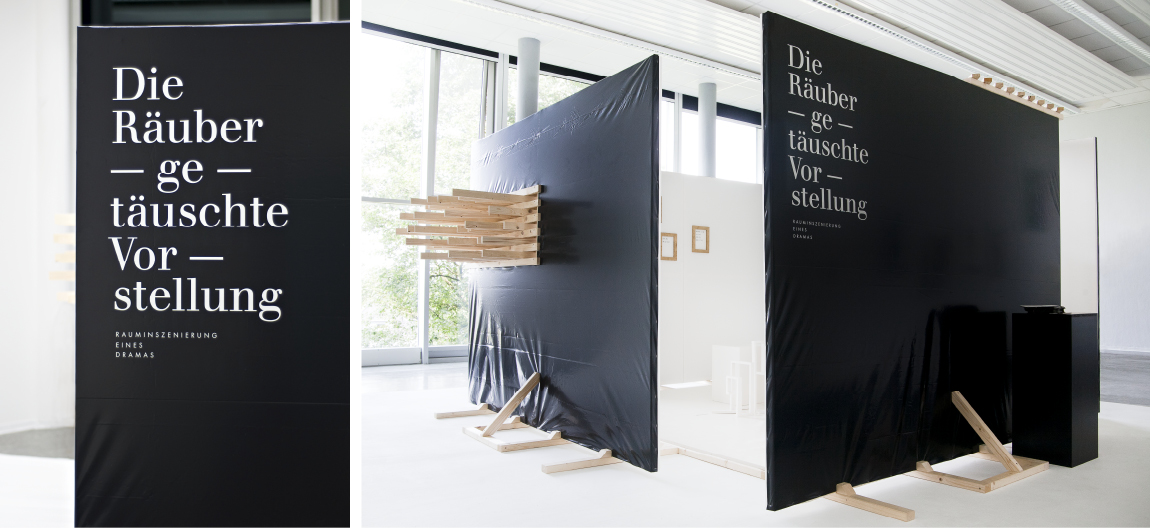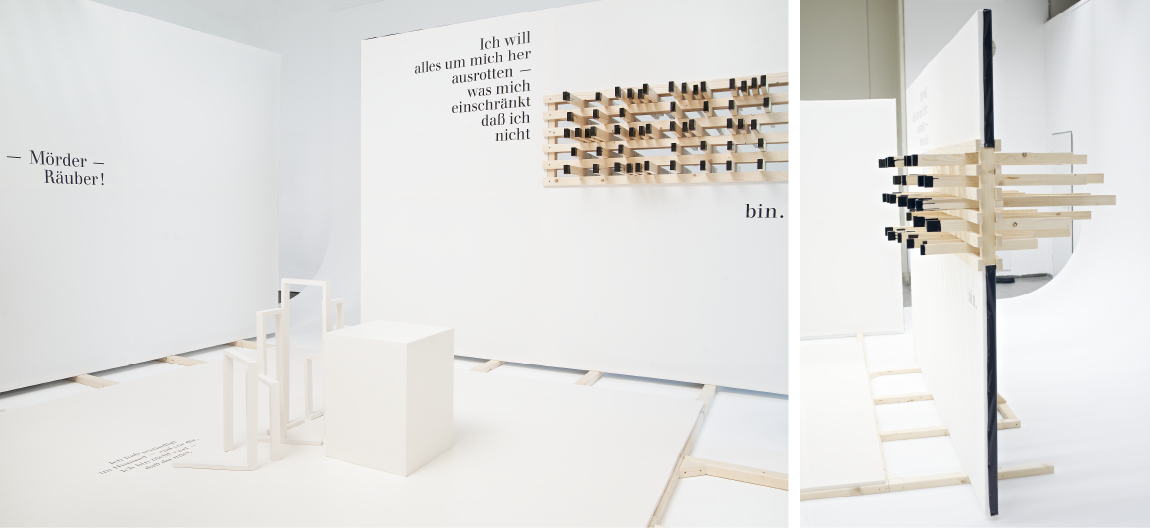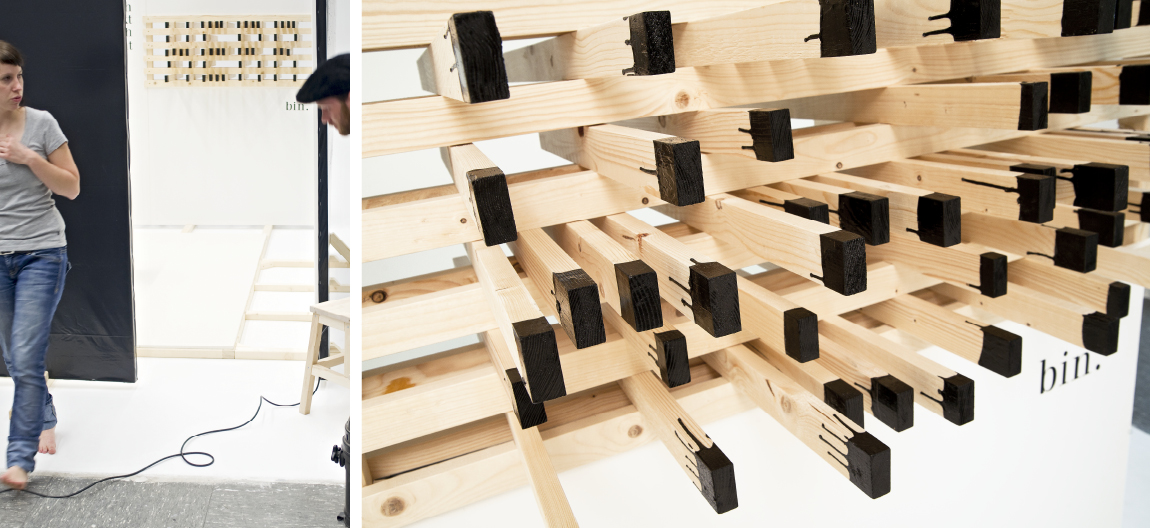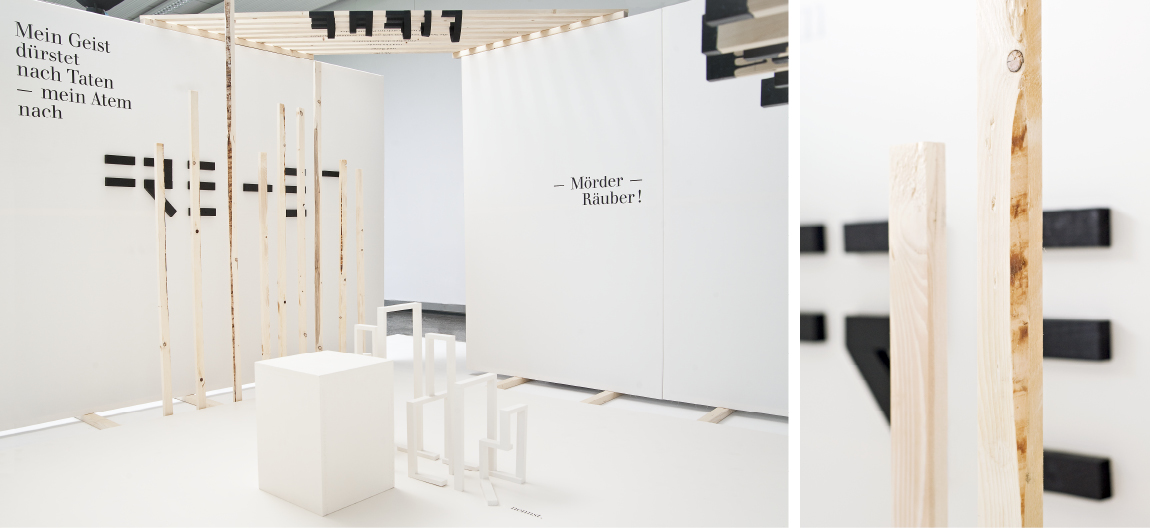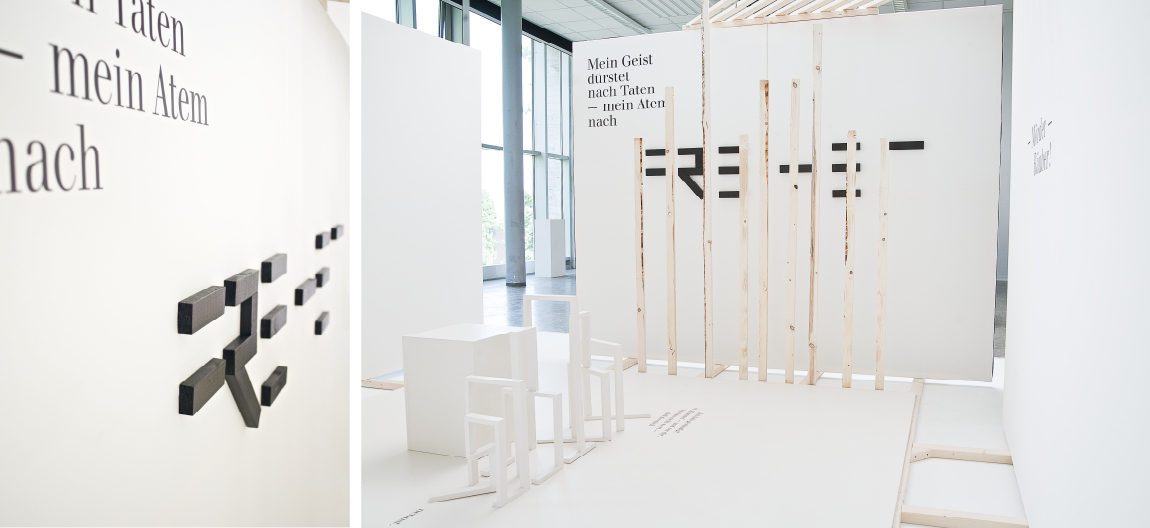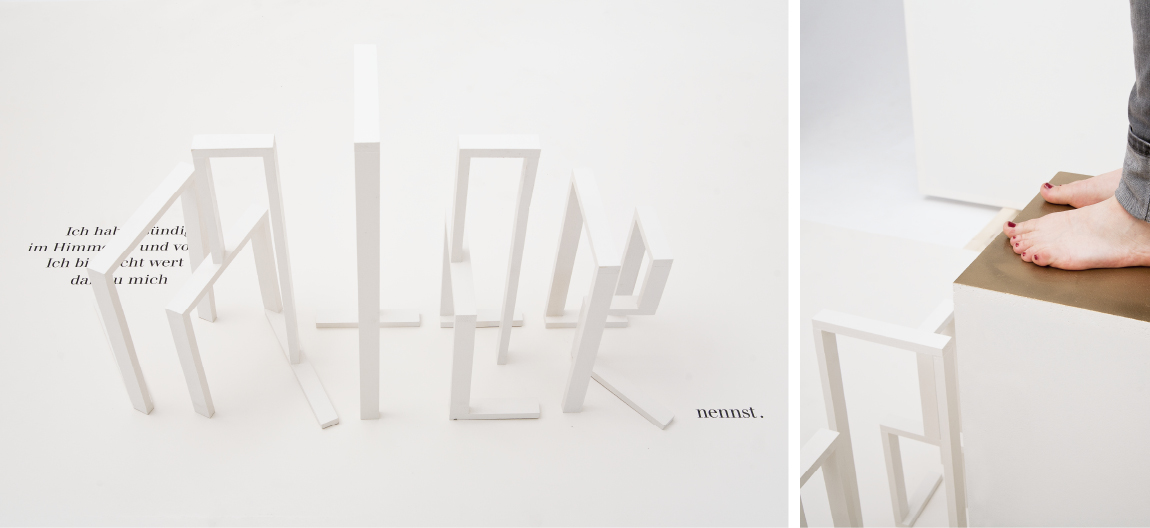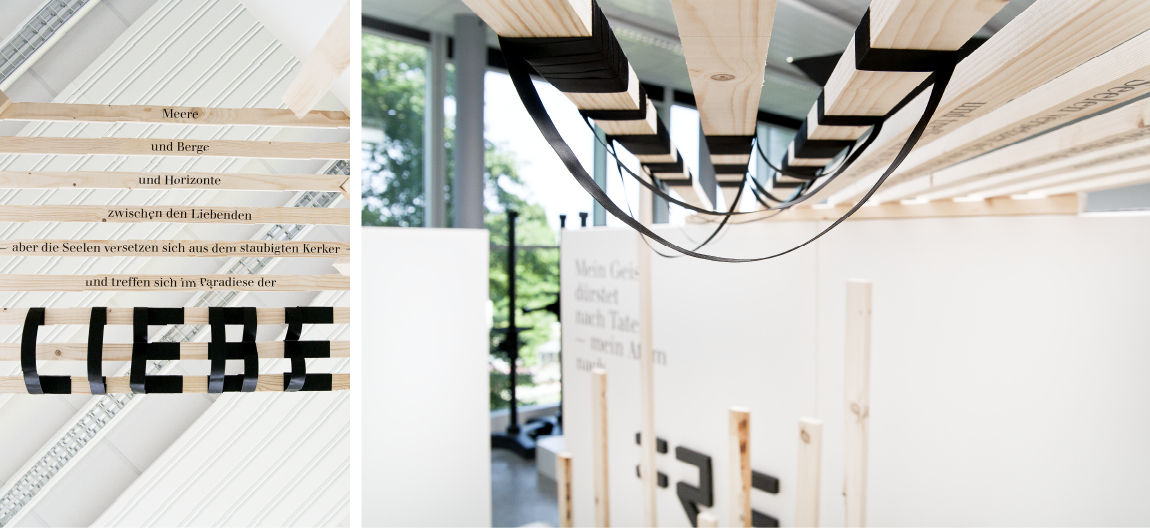
6 Die Räuber — getäuschte Vorstellung — Rauminszenierung eines Dramas Räume Typografie
›Die Räuber — getäuschte Vorstellung‹ entstand im Juli 2010 als Diplomarbeit am Fachbereich Gestaltung der Fachhochschule Bielefeld.
Das Projekt versteht sich als Experiment, ein Theaterstück ohne Schauspieler und ohne das klassische Theaterumfeld zu inszenieren und in Form einer Rauminstallation erlebbar und begehbar zu machen.
Der Fokus der Inszenierung liegt auf dem Aspekt der Täuschung und Enttäuschung, den die vier Protagonisten des Schillerschen Dramas erleben.
Die Hauptdarsteller sind in Form von Zitaten und typografischen Figuren im Raum vertreten und bespielen Decke, Boden und Wände.
Der Raum bildet keine geschlossene Einheit, er zerfällt in einzelne Teile, genau wie die Charaktere im Stück selbst. Jeder ist auf sein eigenes Begehren konzentriert. Dies kann der Betrachter nachvollziehen, indem er einen bestimmten Blickwinkel einnehmen muss, um den figürlich inszenierten Wunsch des Einzelnen zu entdecken.
Form und Größe, Position, sowie das inszenierte Wort selbst, beschreiben den Charakter und seine Rolle in dem Stück.
Melanie Opad
Mal wieder ein gutes Beispiel dafür, wie intelligent man mit Typographie umgehen kann. Verdammt gute Arbeit.
Das nenn ich mal eine richtig tolle Diplomarbeit. Typographie, Installation und Interpretation hervorragend.